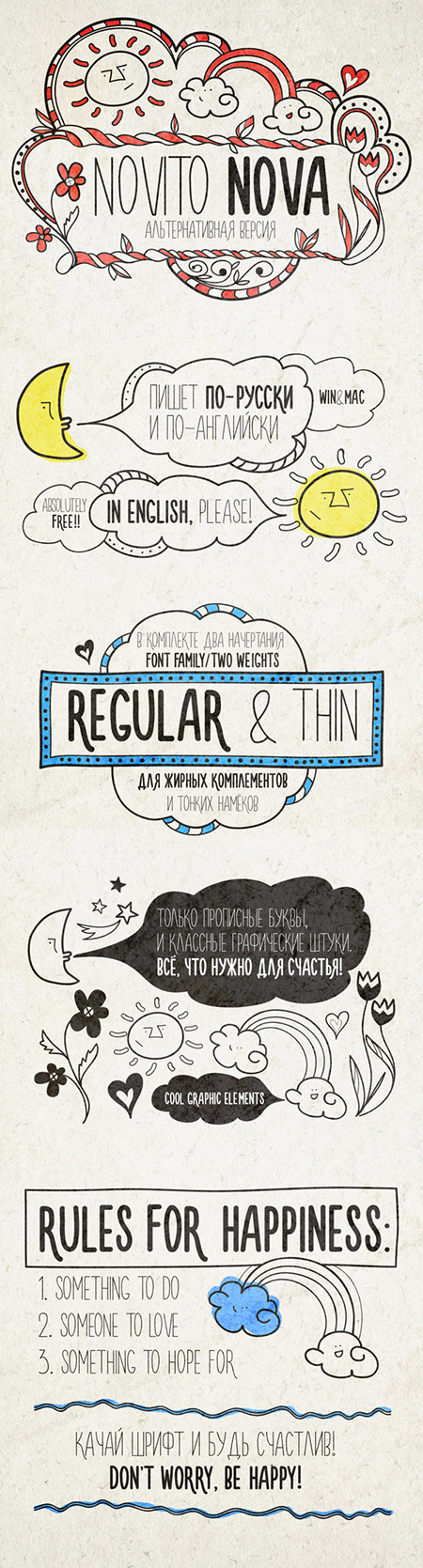
Шрифт - Novito Nova
Замечательный дизайнерский шрифт для забавных комментов и вывесок. Пишет на русском и английском.
Очень классно и креативно преподнесен данный шрифт! Ура создателям))))
Пишет и маленькими, и большими, главное нажать кнопочку "ТТ" или "Тт" (в окне параметров символа). Если ни одна из этих кнопок не зажата, пишет только заглавные,)
Классный, шикарный,великолепный!!!Жалко только что он не пишет маленькими буквами(((
я поняла в чем дело, в этом шрифте только заглавные буквы, остальные просто не отображаются
классный шрифт, жалко у меня не отображается :( буква Д только и цифры
На самом деле нет тут никаих графических штук просто шрифт в двух вариантах, не более и не менее. Так что не стоит покупаться на эти картинки. Очевидно, дама, которая создала этот шрифт использовала дополнительно кисти, только какие и где их взять, она умалчивает. Просто я только что заходила на её сайт, те же самые картинки и никакого обяснения.
Отличное оформление + шрифт на высоте.
А какие графические "штуки"?